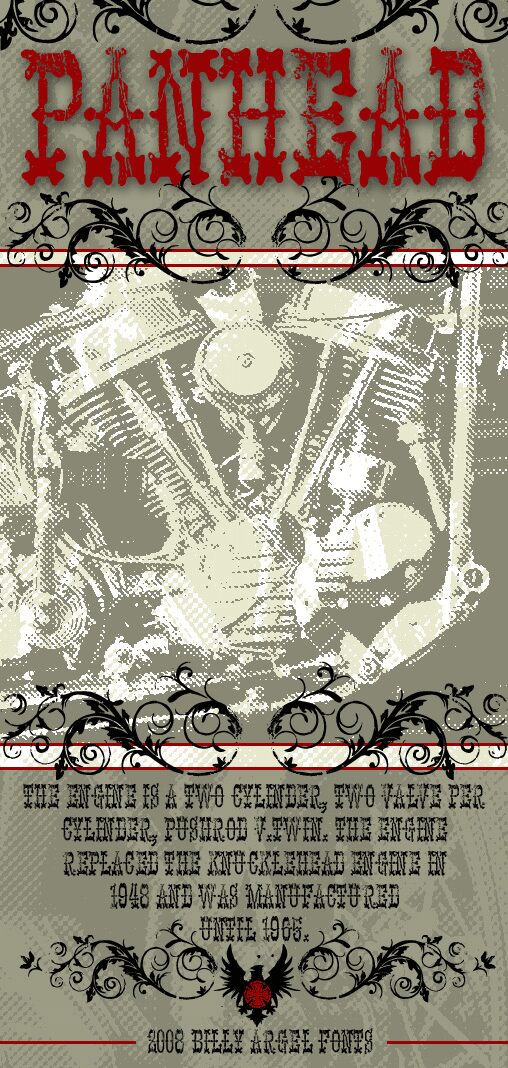
Panhead autorstwa Billy’ego Argela to darmowy font display w stylu westernowym, z erozją i zakurzonym klimatem dawnych plakatów. Litery wyglądają jednocześnie na sfatygowane i ozdobne, a ich klockowate kształty w stylu dawnych salonów oraz ostre, chropowate krawędzie sprawiają, że krój sprawia wrażenie naturalnie zniszczonego, a nie tylko „postarzonego” filtrem.
Świetnie sprawdzi się na ulotkach z rodeo, etykietach whisky, plakatach zespołów czy w reklamach stylizowanych na dawne witryny sklepowe – wszędzie tam, gdzie darmowy font ma dodać charakteru, nie tracąc przy tym historycznego sznytu. Wykorzystaj go do krótkich nagłówków lub inicjałów, zwłaszcza gdy chcesz, by klimat Dzikiego Zachodu bił bezpośrednio z liter, zamiast z dodatkowych ozdobników.